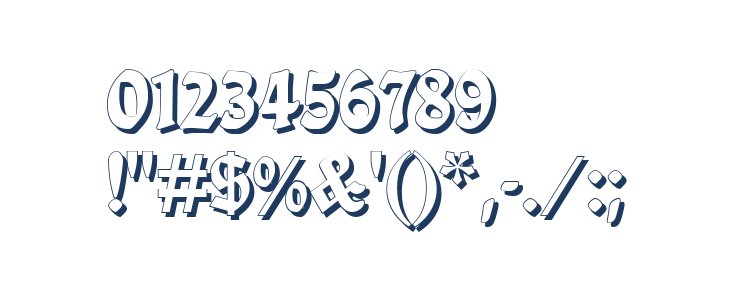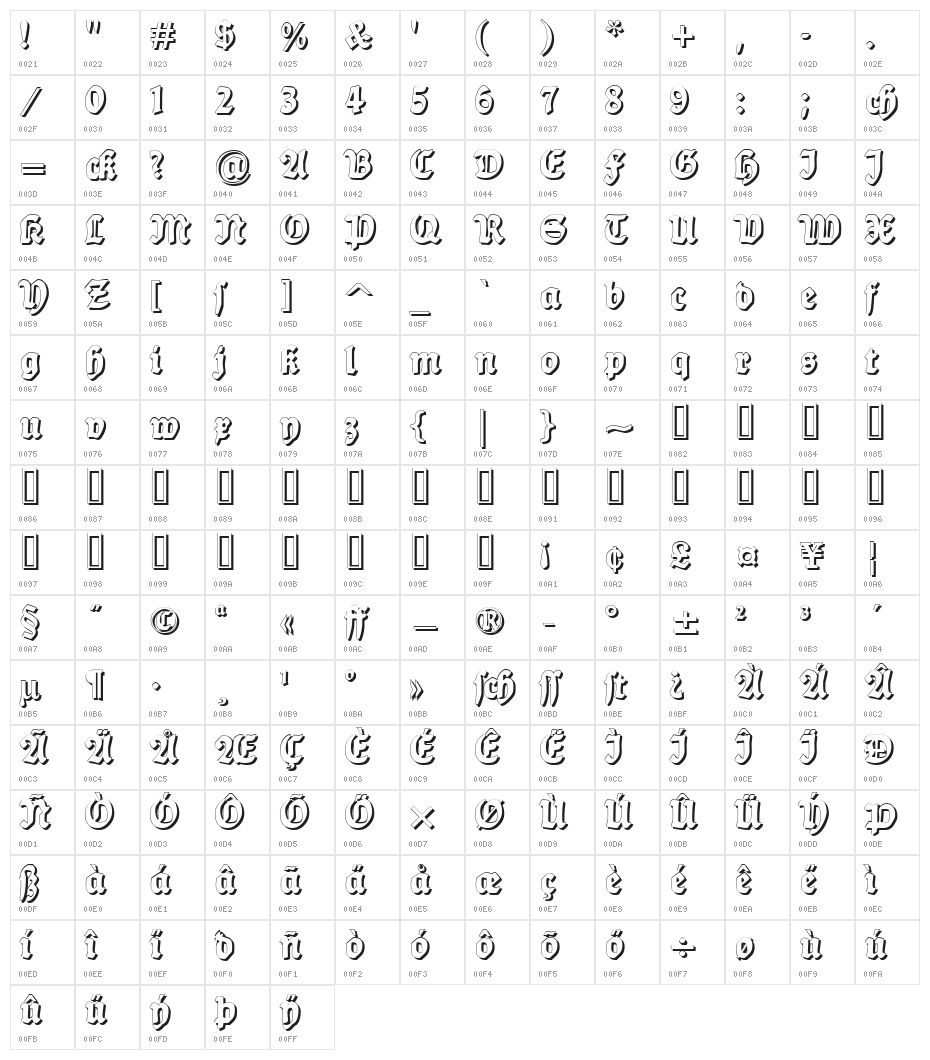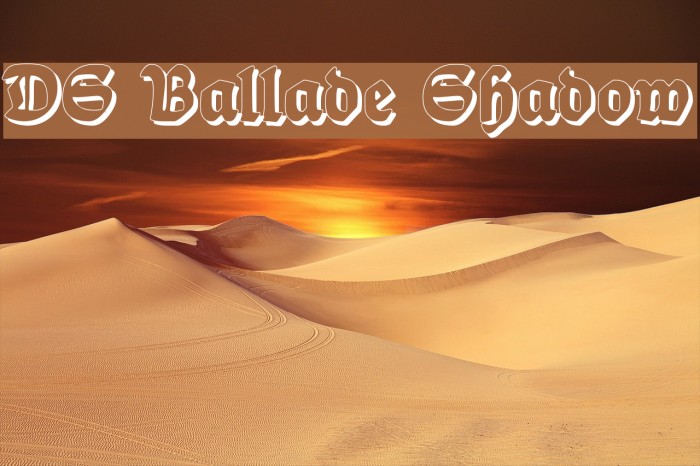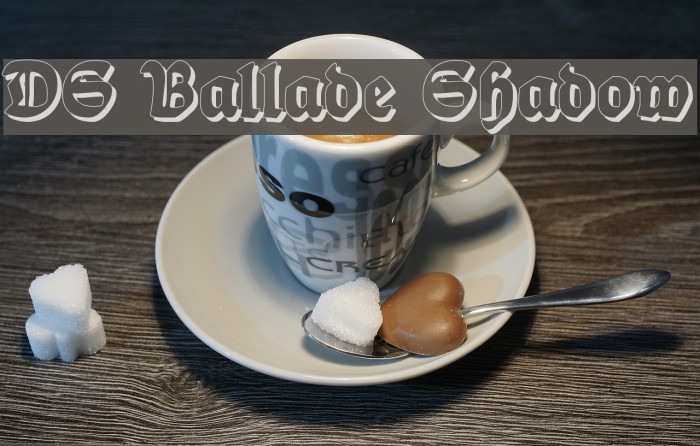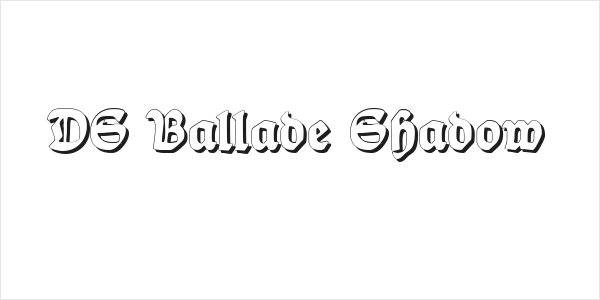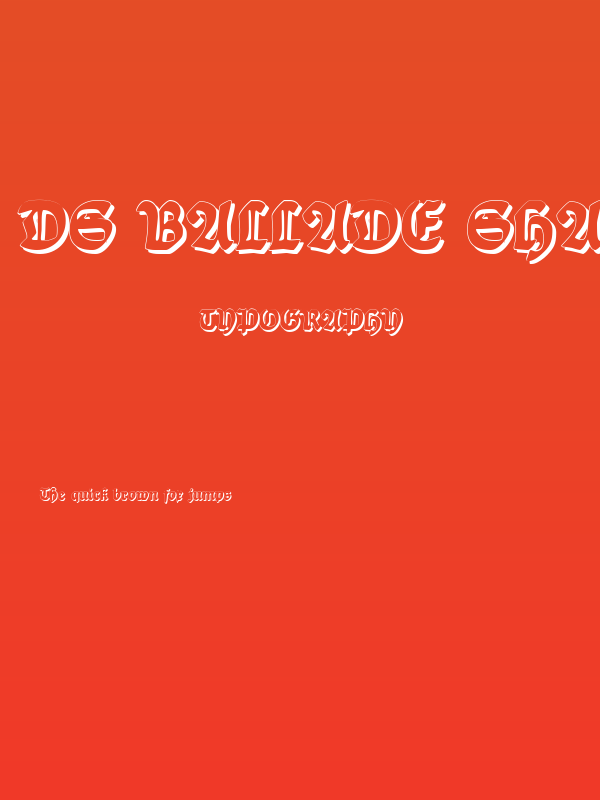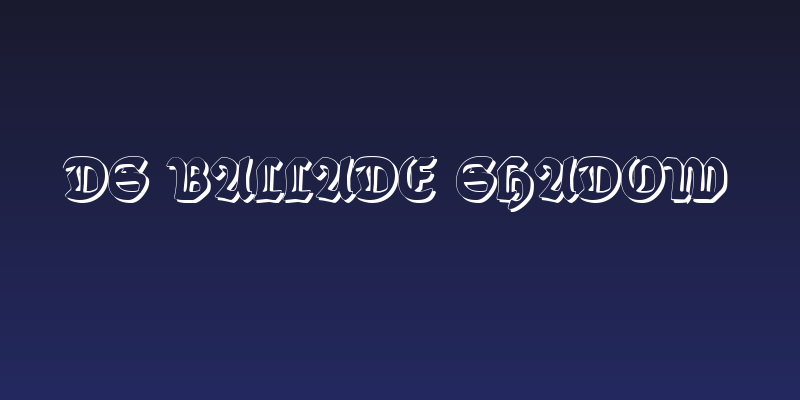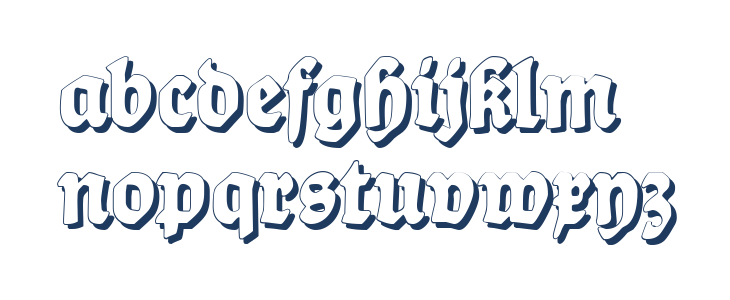
DS Ballade Shadow Font
✎ Gothic
| Caso d'uso | Headlines, Logos, Decorative text |
| Progetti proposti | Ideal for vintage-themed posters, book covers, branding for historical or fantasy projects, and decorative signage. |